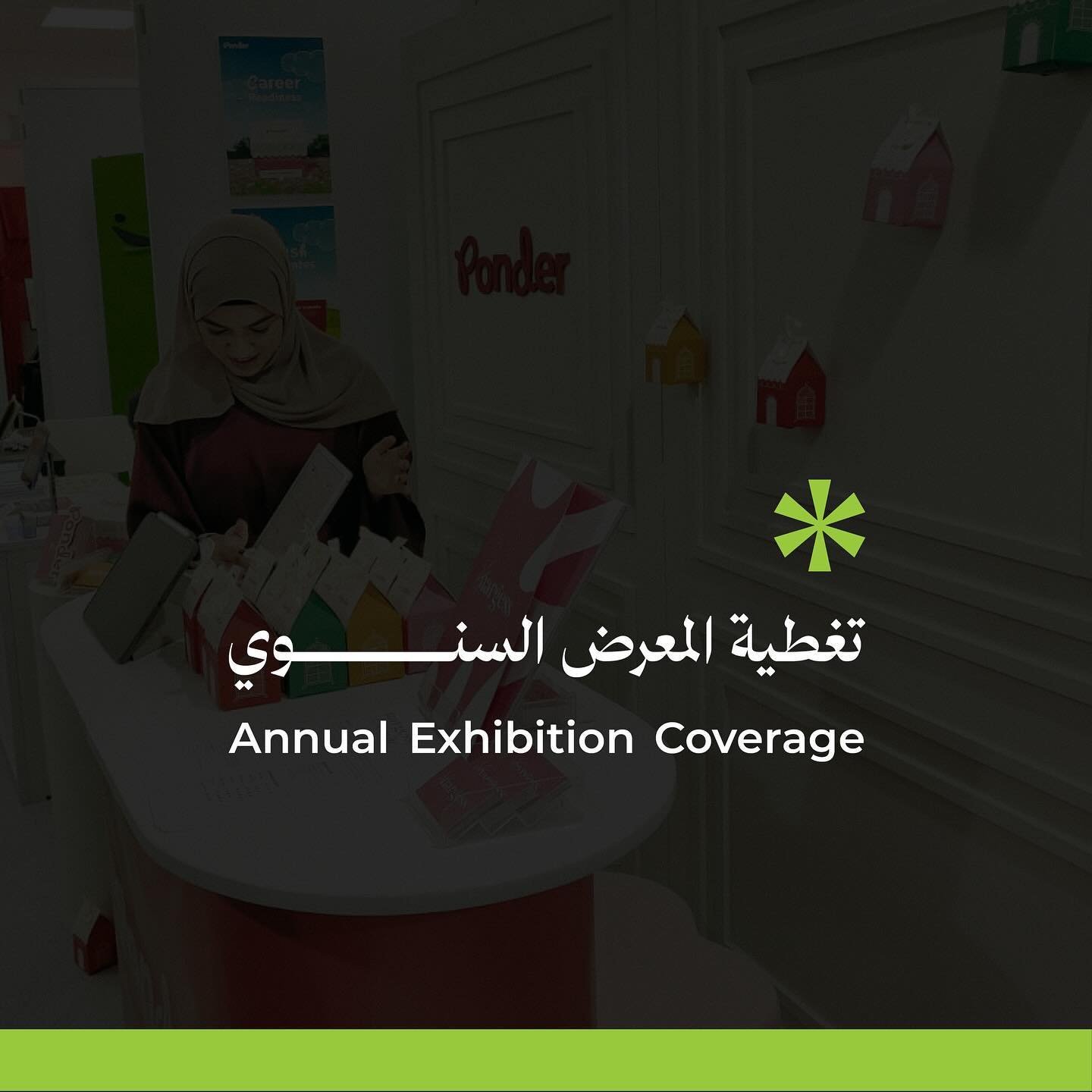
استخدام خط فاطمة عربي -Annual Graduates Exhibition
فاطمة عربي هو خط طباعي عربي حديث يستلهم من أسلوب الخط النسخ، ويتميز بتباينه العالي ونسبه المتقنة. فاطمة عربي يعتبر خيارًا مثاليًا لمجموعة واسعة من الاستخدامات، سواء في الطباعة أو الوسائط الرقمية أو الشاشة.